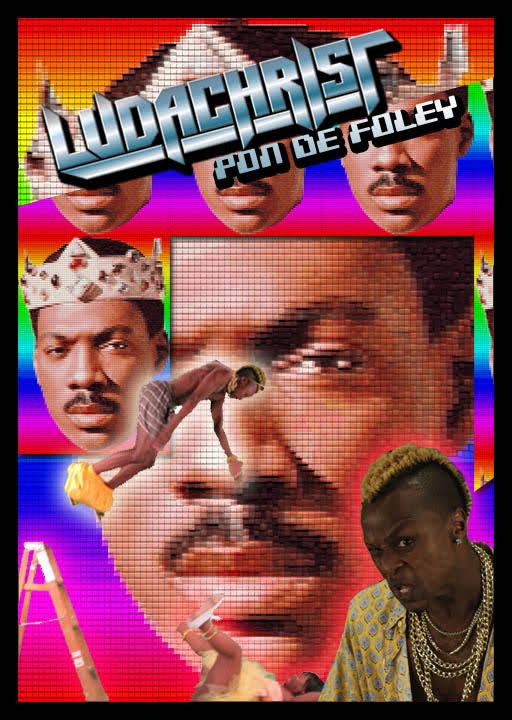
Eckige/schnittige Schrift
kommt mir irgendwie bekannt vor...
Ist das nicht sogar Freeware? Eventuell nachträglich etwas verändert?
Der 3D-Judachrist ist sicher "handmade": schau dir z.B. mal die L-U-Verbindung an... und so abartig billig wie die ganze Grafik gestaltet ist, möcht ich mich nicht damit befassen müssen ...
Es gibt schon solche Fonts, wobei ich bei deinem Beispiel auch glaube dass das handgemacht ist.